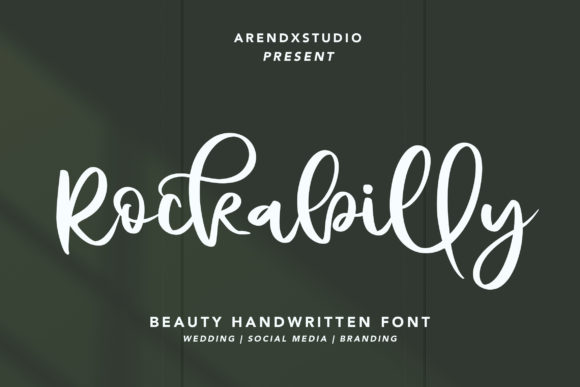
[Creativefabrica] Rockabilly Font (2021)
Rockabilly - это свободный рукописный шрифт, созданный для упаковки продукции, пригласительных открыток, флаеров, плакатов для мероприятий, макетов продукции и многого другого. С помощью этого профессионального шрифта вы получите высококачественный конечный результат.